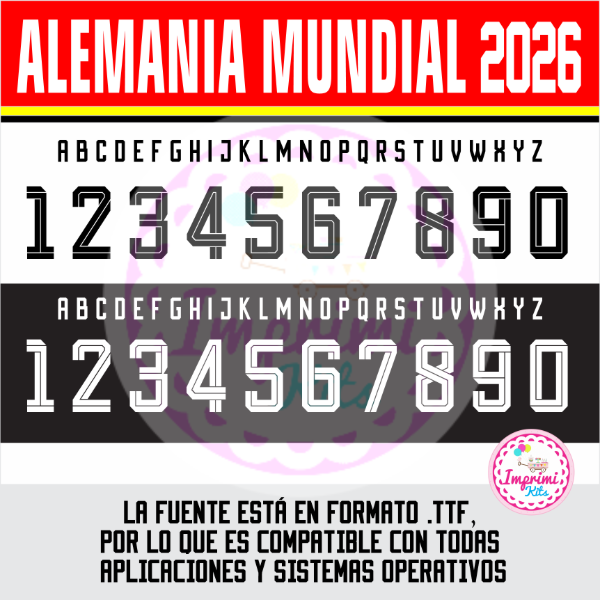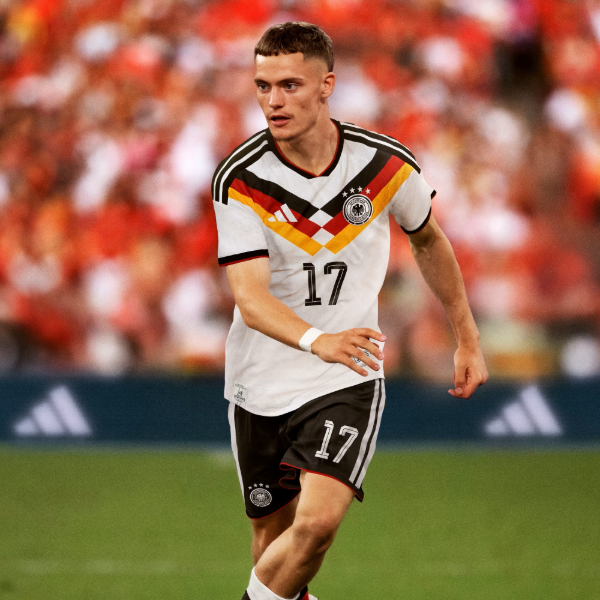
Tipografia Alemania 2026 Mundial Camisetas Ttf Dorsal Números DTF
Tipografía Números Fuente
Realizá todo tipo de creaciones con la tipografía utilizada actualmente en el club